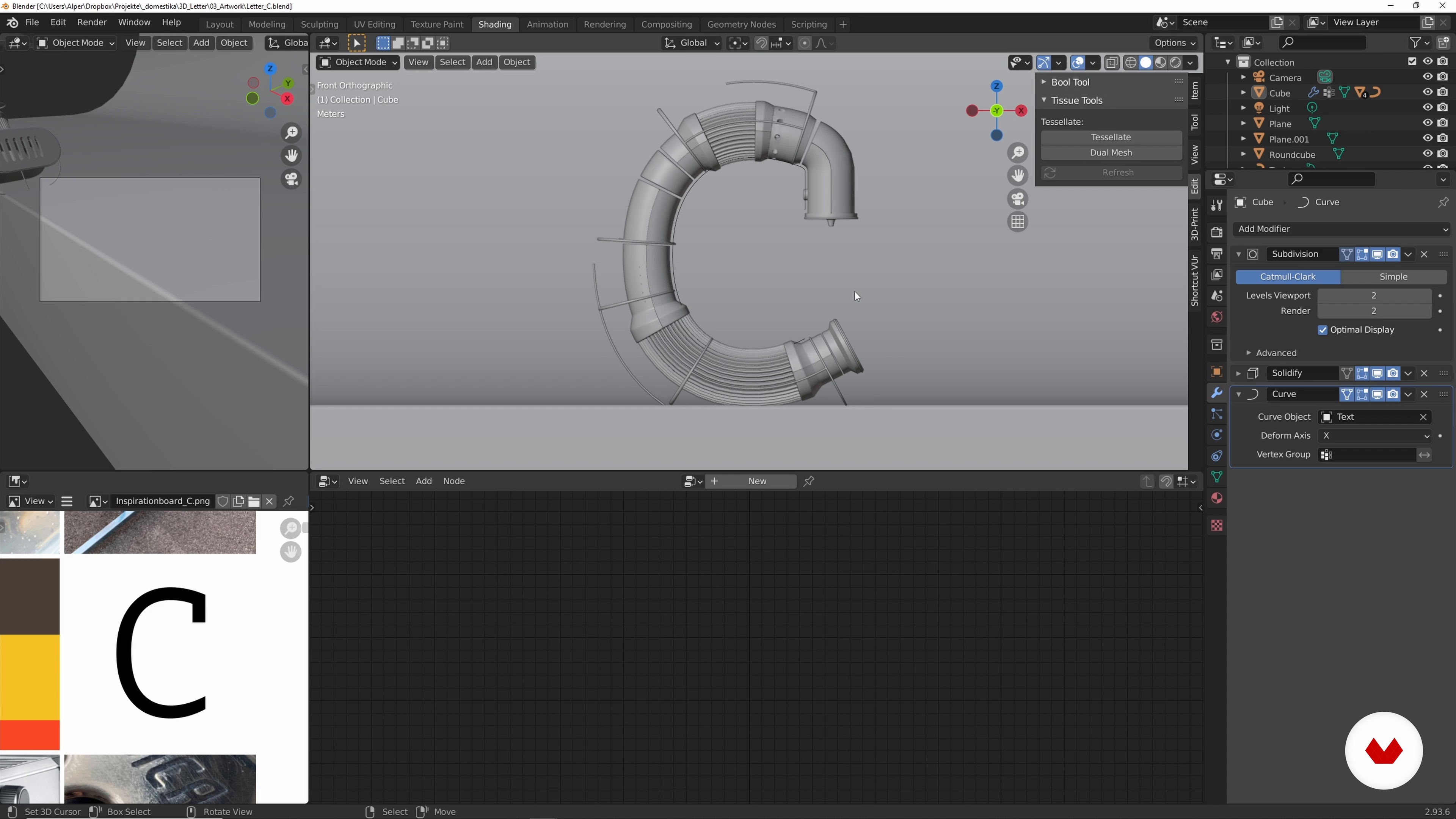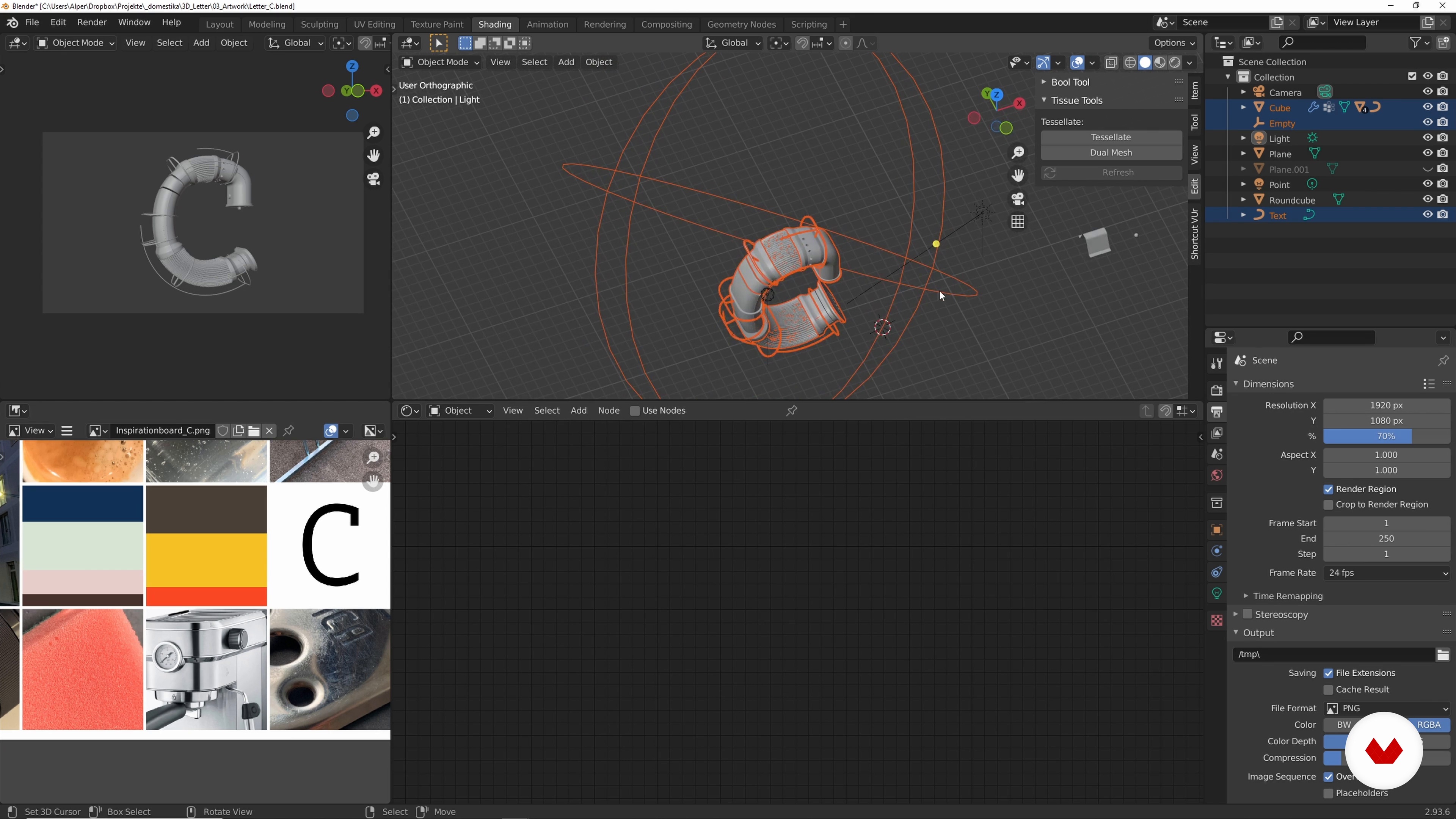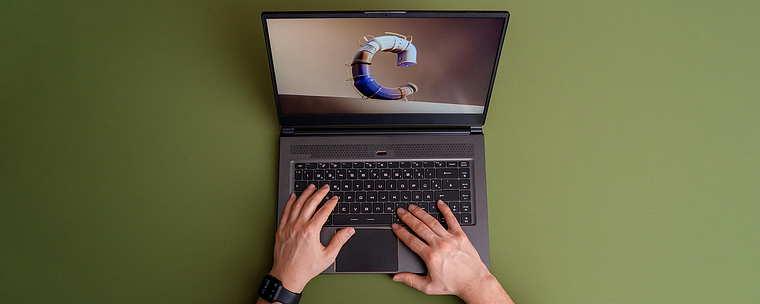
In den Werken von Designer und 3D-Künstler Alper Dostal verhalten sich Objekte und Materialien aus unserem Alltag irgendwie anders. Er liebt es, Elemente wie Buchstaben aus ihrem Kontext zu ziehen und daraus ein spannendes Kunstwerk zu modellieren. Im Spiel mit Kontrasten, zum Beispiel zwischen industriellen und organischen Elementen, hat er seinen Stil gefunden.
Lerne, einen Buchstaben zu gestalten, der nicht nur gut aussieht, sondern auch eine kleine Geschichte erzählt. Alper zeigt dir in diesem Onlinekurs, wie er ein Projekt vorbereitet, von der Inspirationssuche bis zur Entscheidung für ein Farbschema. Lass deinen Buchstaben in einem modularen Aufbau in Blender Form annehmen und entdecke, wie du prozedurale Texturen erstellen, harmonische Materialien und Farben anwenden und dein Design am Ende elegant in Szene setzen kannst.
Zu Beginn lernst du Alper Dostal kennen. Er erzählt von seinem bisherigen Werdegang und wie er dazu kam, sich auf den Bereich 3D-Design zu spezialisieren. Außerdem zeigt er dir, welche Einflüsse seinen Stil geprägt haben.
Zur Vorbereitung deines Designs zeigt dir Alper, wie du Inspiration finden und Ideen generieren kannst. Du suchst nach Referenzen, Materialien, Formen, Texturen und Farben, überlegst dir ein Thema für deinen Buchstaben und sammelst alles in einem Moodboard als Basis für die spätere Gestaltung.
Anschließend lernst du, wie Alper Blender konfiguriert, um seinen Workflow zu optimieren. Du beginnst, Basisformen zu modellieren, aus denen du mithilfe des Curve-Tools deinen Buchstaben formen kannst. Dann lernst du, wie du Farben harmonisch anwendest und mithilfe von prozeduralen Texturen Materialien beziehungsweise Shader erstellen kannst.
Jetzt geht es an die Inszenierung und Beleuchtung deines Buchstabens: Alper hilft dir, die richtige Kameraposition zu finden. Dann setzt ihr verschiedene Lichtquellen und experimentiert mit Lichtfarben und -intensität für eine interessante Beleuchtung.
Um dein Bild realistischer wirken zu lassen, fügst du verschiedene Effekte hinzu und optimierst dein Projekt zum Rendern. Anschließend zeigt dir Alper, wie er letzte Details in Photoshop bearbeitet. Zum Abschluss lernst du, welche Vorteile die Arbeitsweise mit Modulen dir beim Modellieren deiner eigenen Projekte bietet.
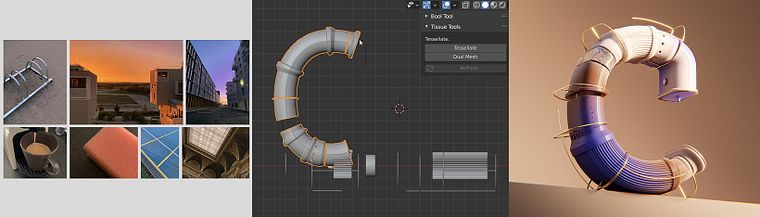
Dieser Kurs eignet sich für alle, die lernen wollen, 3D-Objekte in einem modularen Aufbau zu modellieren und mit Farb-, Textur- und Formkontrasten zu experimentieren.